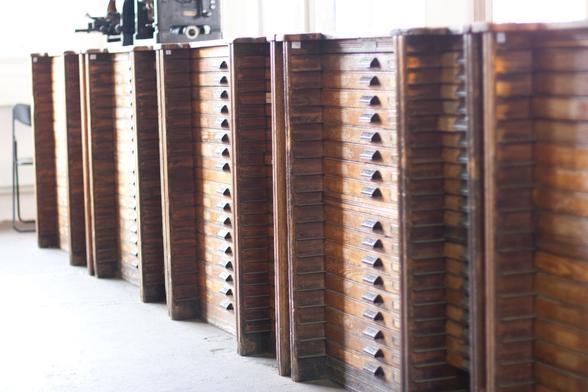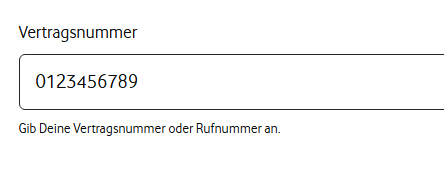
Ich bin ja echt kein #Typografie-Nerd, aber: Hey Vodafone, was *stimmt* nicht mit euch?
Ja, ich kenne Mediävalziffern, wo die Ziffern absichtlich unterschiedliche Höhen haben (siehe Link).
Aber erstens ist der Höhenunterschied hier so klein dass es wie ein Fehler wirkt und nicht wie Absicht.
Und zweitens sollte es dann *zwei* verschiedene Höhen geben, nicht *drei*. 🤦‍♂️
Eingabefeld "Vertragsnummer". Als Beispielwert wurden die Ziffern 0 bis 9 eingetragen. Die Ziffern 0, 2, 6, 8 und 9 sind normal hoch. 1, 3, 5 und 7 sind etwas niedriger. Und die 4 ist nochmal niedriger!
@CCC Ist das mit den fehlenden Unterlängen in den Titeln ein Problem mit dem Font oder sieht das nur bei mir so komisch aus? #typografie
Screenshot des Fahrplans mit zwei Einträgen bei denen die Unterlängen der Buchstaben fehlen.
@janboehm Falls du vorhaben solltest das weiter zu verwerten, will sich dein Team vielleicht auch mit der gebrochenen Schrift hier befassen. Nazis scheitern nämlich praktisch immer daran, die doitsche #Fraktur zu identifizieren und verwenden meist stattdessen die sehr undeutsche #Textura (oft #OldEnglish genannt).
Bin Laie, aber auch das hier scheint mir eine kunstvollere Form davon zu sein.
Ligaturen sind kein typografisches Tieffluggebiet und die Lektoren der Süddeutschen sind leider keine Kampfflugzeuge im Widerstand gegen terroristisch falsch gesetze Ligaturen. 🤭
Das Wort "Rubrik" kommt von den Rubrikatoren, das waren im Mittelalter die Schreiber, die die besonderen roten Lettern und Anfangsbuchstaben in die Bücher geschrieben haben, die den Anfang eines Kapitels markierten.
"Ruber" ist lateinisch für rot. "Rubricare" = rot Färben.
(gelernt im Gutenberg-Museum in Mainz)
Ich mag ja gute #Typografie. Z. B. befindet sich hier zwischen dem "Z." und dem "B." ein schmales geschütztes Leerzeichen. Der Unterschied ist minimal, der Aufwand, es einzugeben, dafür maximal.
Zusätzlich sehr empfehlenswert sein Podcast #54 zum Thema Typografie für Fotograf:innen unter schlicksbier.com/podcast/
Unheimlich motivierend und mit vielen hilfreichen Infos gespickt.
"Könnten ch und sch jeweils ein Buchstabe sein?" @typojournal:
"Mitte des 19. Jahrhunderts schlugen Prof. Dr. Gutav Michaëlis und andere Einzelbuchstaben vor, die ch und sch in deutschen Texten ersetzen sollten. Es erschienen auch verschiedene Drucksachen mit entsprechenden, eigens geschnittenen Bleisatzbuchstaben. Eine gute Idee oder übereifriges Reformbestreben? Ein Blick zurück auf eine in Vergessenheit geratene Idee."
Erste Runde meiner KI-Typografie-Experimente mit Adobe Firefly.
Faszinierend zu sehen, wie stark sich Material, Licht und Form über Prompts steuern lassen.
Dieses flauschige „Z“ ist der Anfang einer kleinen Alphabet-Serie.
Triggerwarnung für Freunde der detailverliebten Typografie.
Werbeschild für
LCMT
Lecomte
Das O ist verrutscht, leicht nach oben und links.